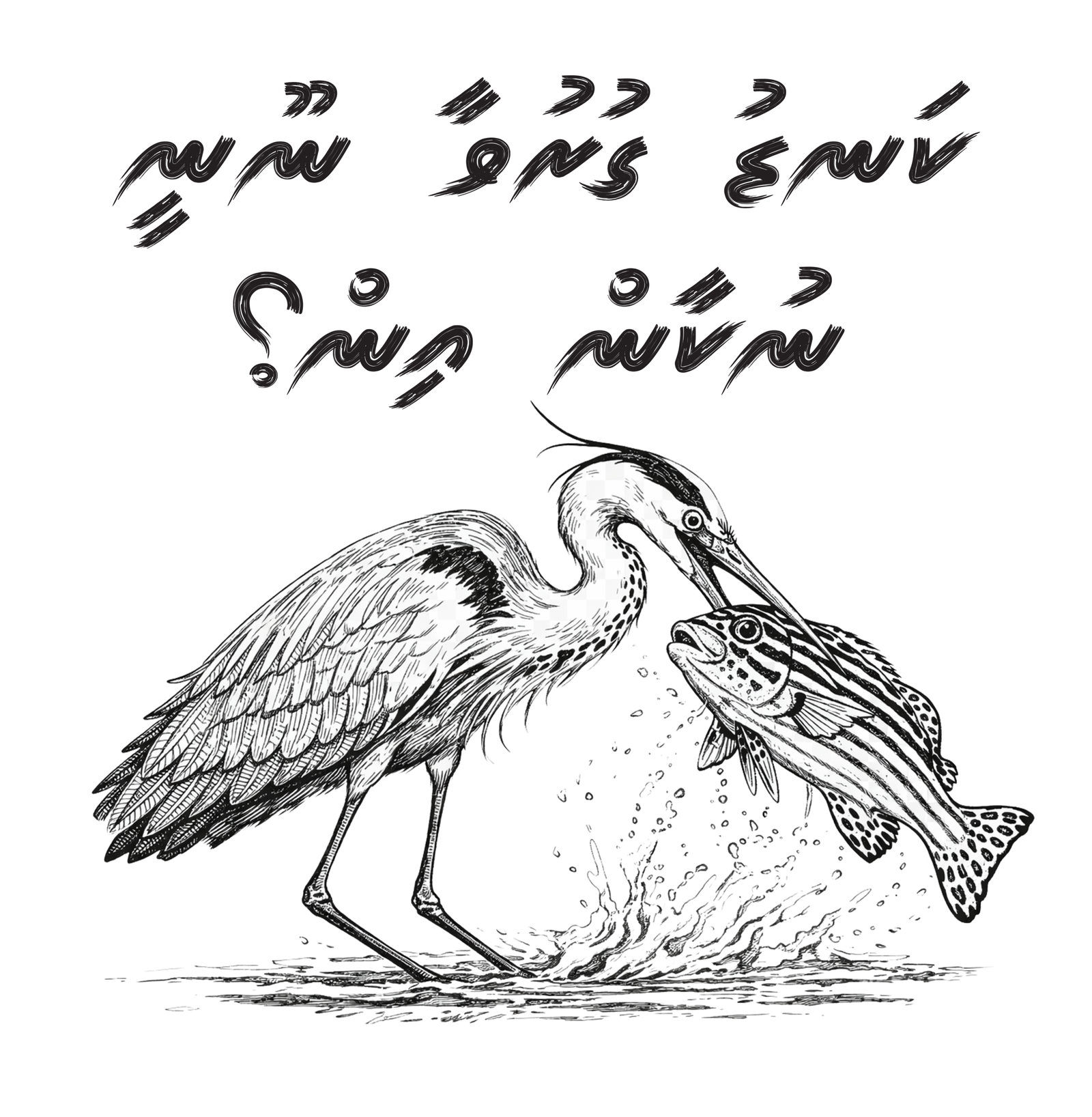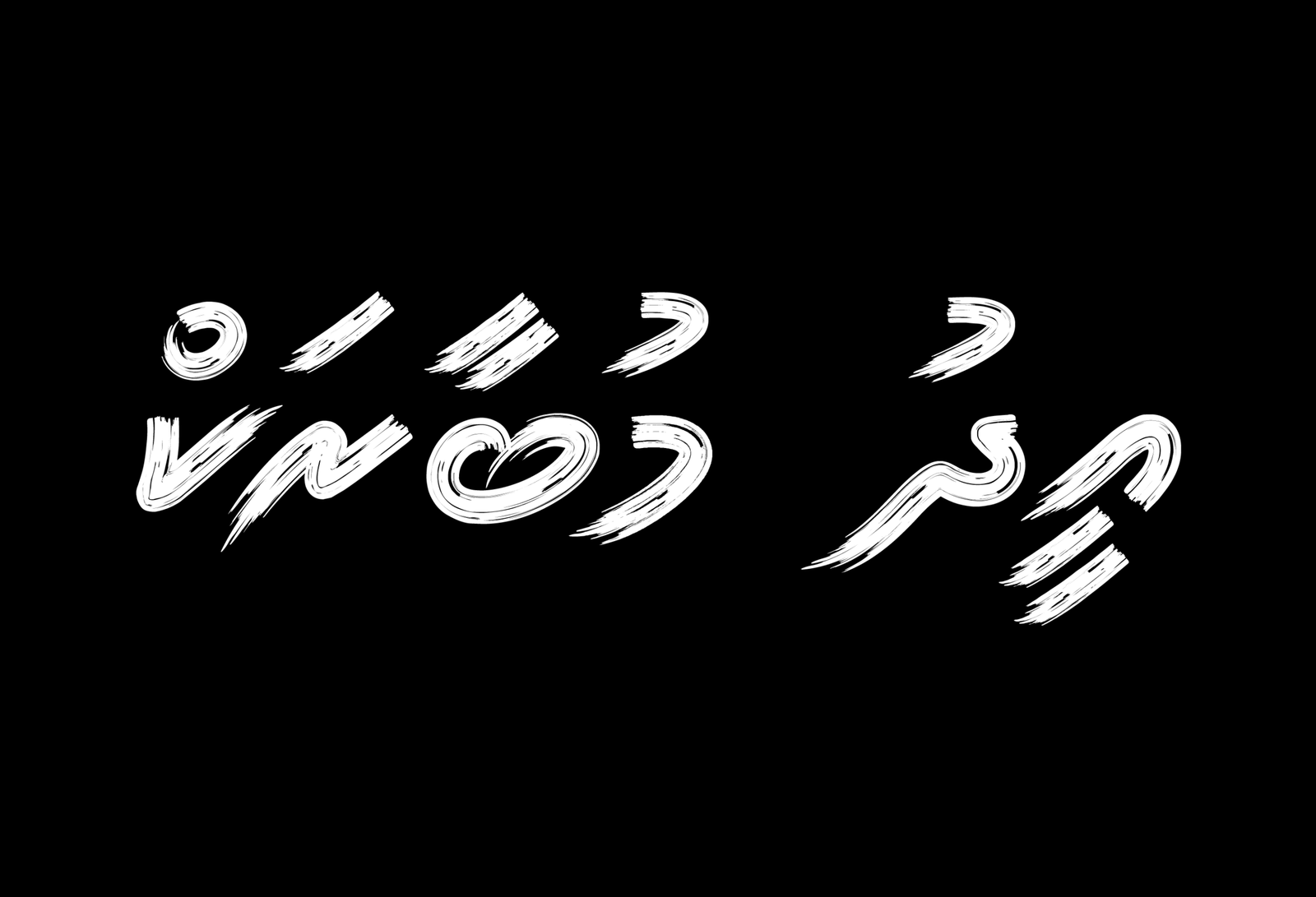
އެމްވީ އިޒީ ފިހި
އެމްވީ އިޒީ ފިހި މި ފޮންޓަކީ ސުރުޚީ އަދި ކުރު ލިޔުން ކޮޅުތަކުގައި ބޭނުން ކުރަން ހަދާފައިވާ ފޮންޓެކެވެ. ދިގު ލިޔުންތަކުގައިވެސް ބޭނުން ކުރެވިދާނެއެވެ. އެކި ދުވަސްތަކުގެ ކާޑު ފަދަ ތަކެތި ހަދާއިރު ދުވަހުގެ ނަން ޖެހުން ފަދަ ކަންކަމަށް މި ފޮންޓް ބޭނުން ކުރެވިދާނެއެވެ. ފިހި ފޮންޓް ހެދިފައި މިވަނީ ކުލަ ފިހިން ލިޔާއިރު ހުންނާނެ ގޮތައް ބަލައިގެންނެވެ.